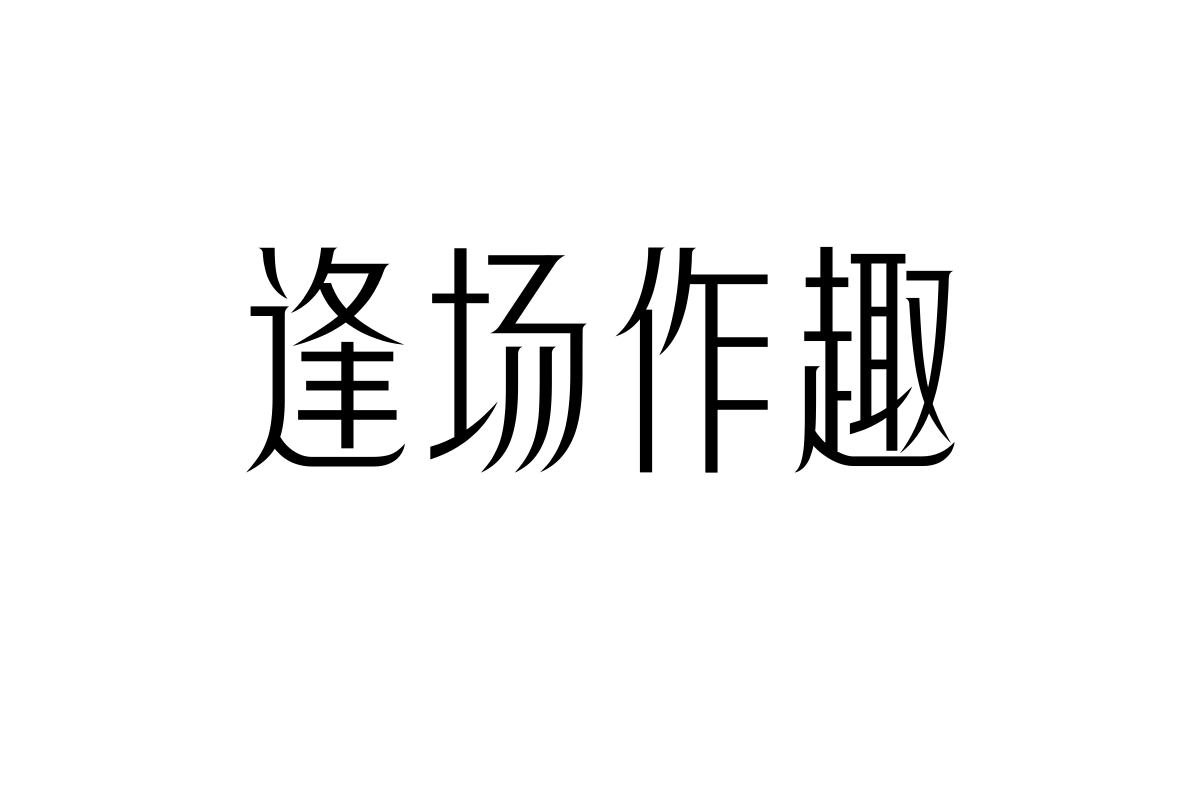
上首芊芊体是一种字体,其特点如下:
1. 字形结构:上首芊芊体的字形结构独特,笔画流畅,线条优美。每个字的笔画都经过精心设计,使得整个字体显得优雅而富有艺术感。
2. 字体风格:上首芊芊体具有独特的书法风格,线条粗细变化丰富,既有粗犷豪放的气势,又有细腻精致的美感。这种风格使得上首芊芊体在视觉上给人一种强烈的冲击力和艺术享受。
3. 适用范围:上首芊芊体适用于各种场合,如广告、海报、书籍、杂志等。它的应用范围非常广泛,能够满足不同用户的需求。
4. 设计特点:上首芊芊体的设计特点在于其独特的字形结构和风格,使得整个字体显得与众不同。同时,它也注重实用性,能够适应各种应用场景,满足用户的个性化需求。
总的来说,上首芊芊体是一种独特而富有艺术感的字体,它的字形结构、风格和设计特点都使其在视觉上给人留下深刻的印象。